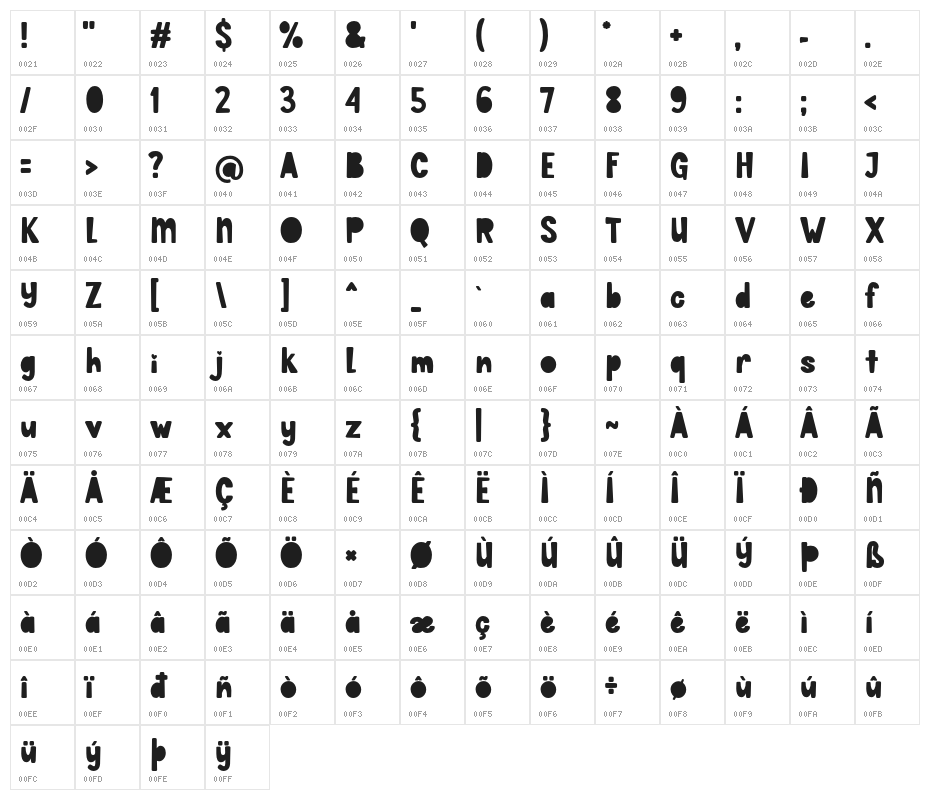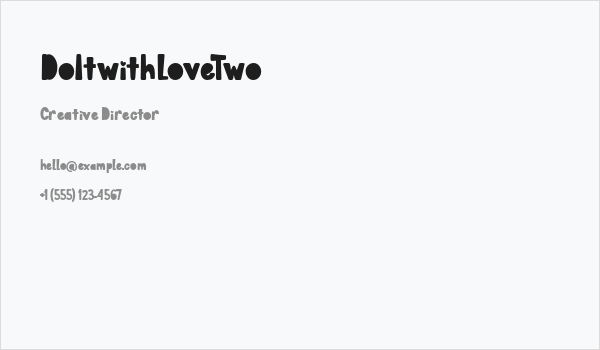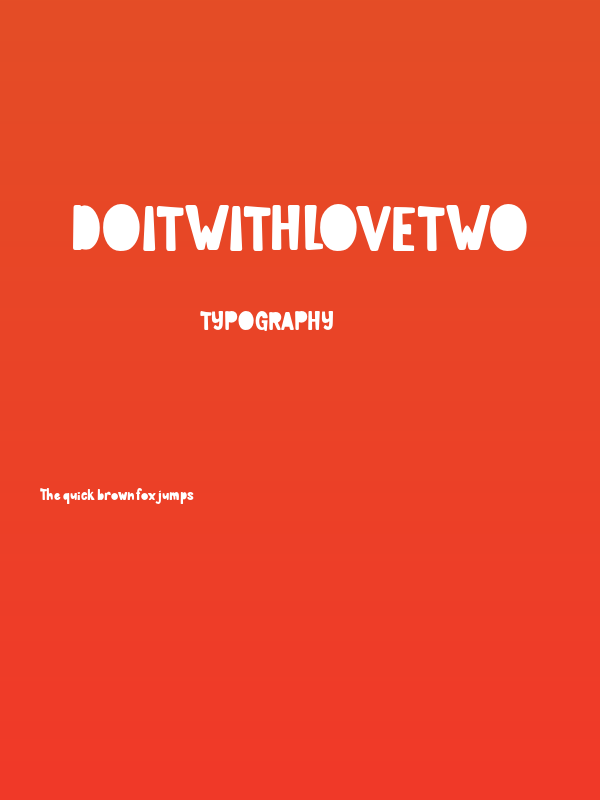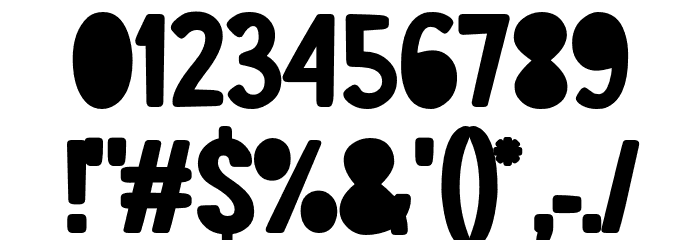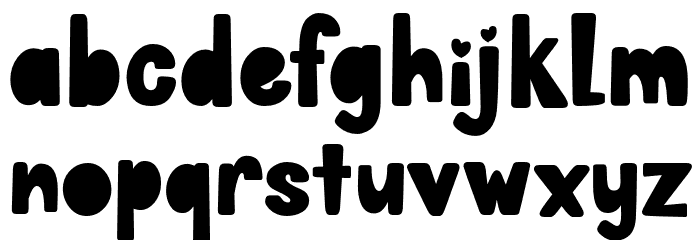
DoItwithLoveTwo Font
| 全体的なスタイル | Playful, Whimsical |
| おすすめプロジェクト | Ideal for children's books, playful branding, greeting cards, and creative posters. |